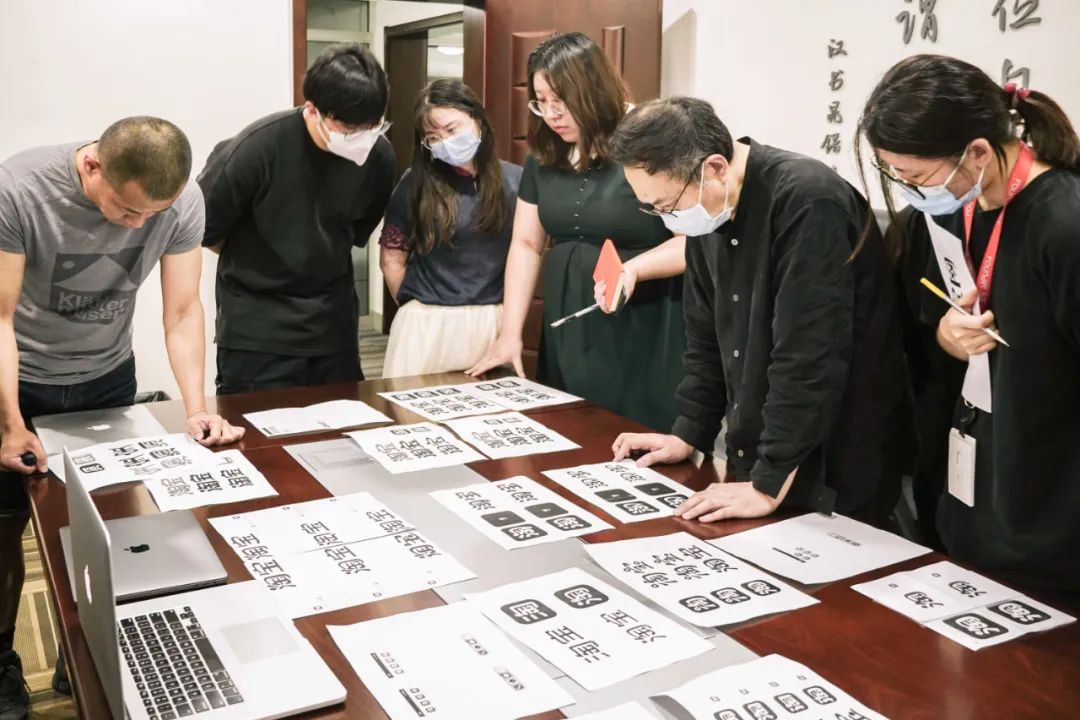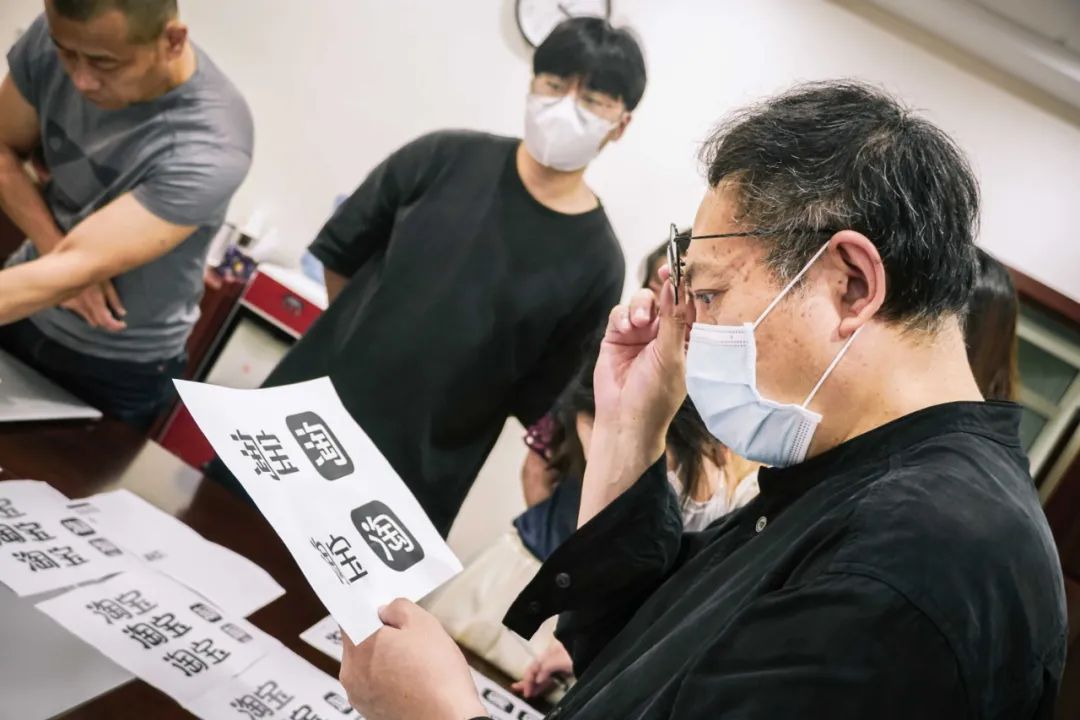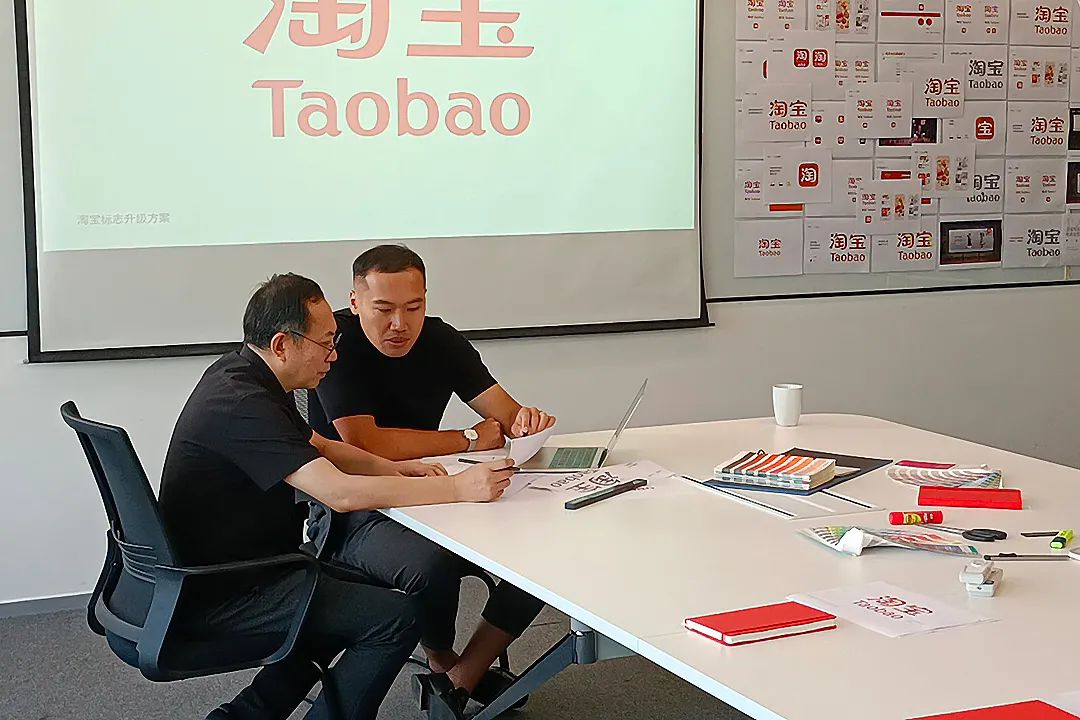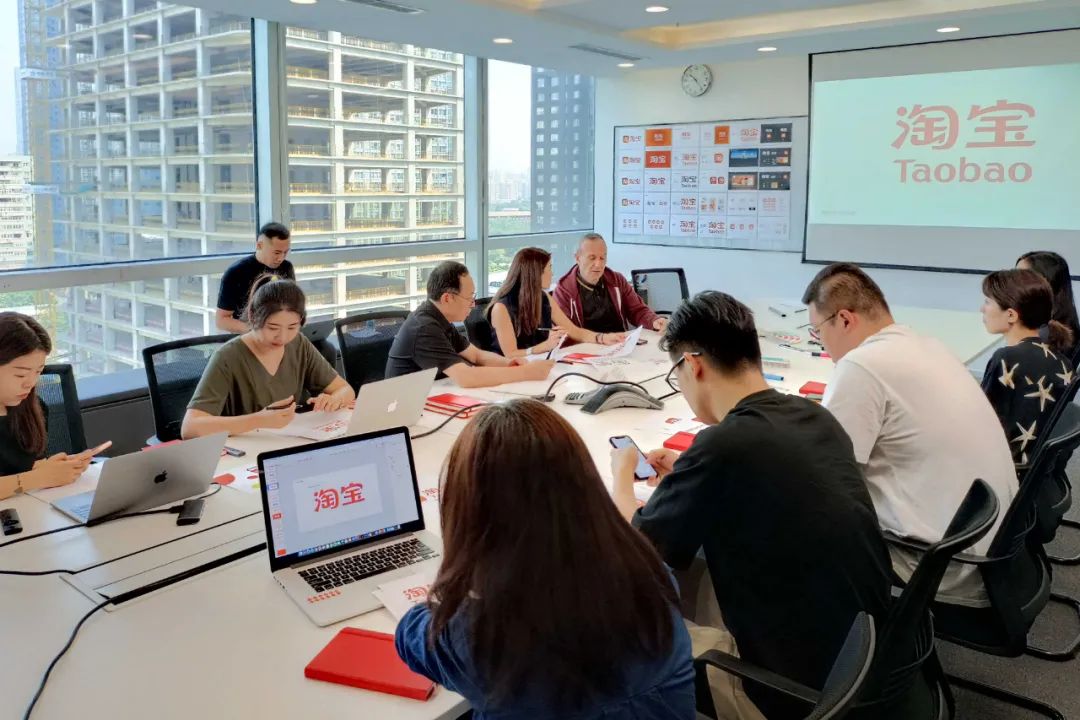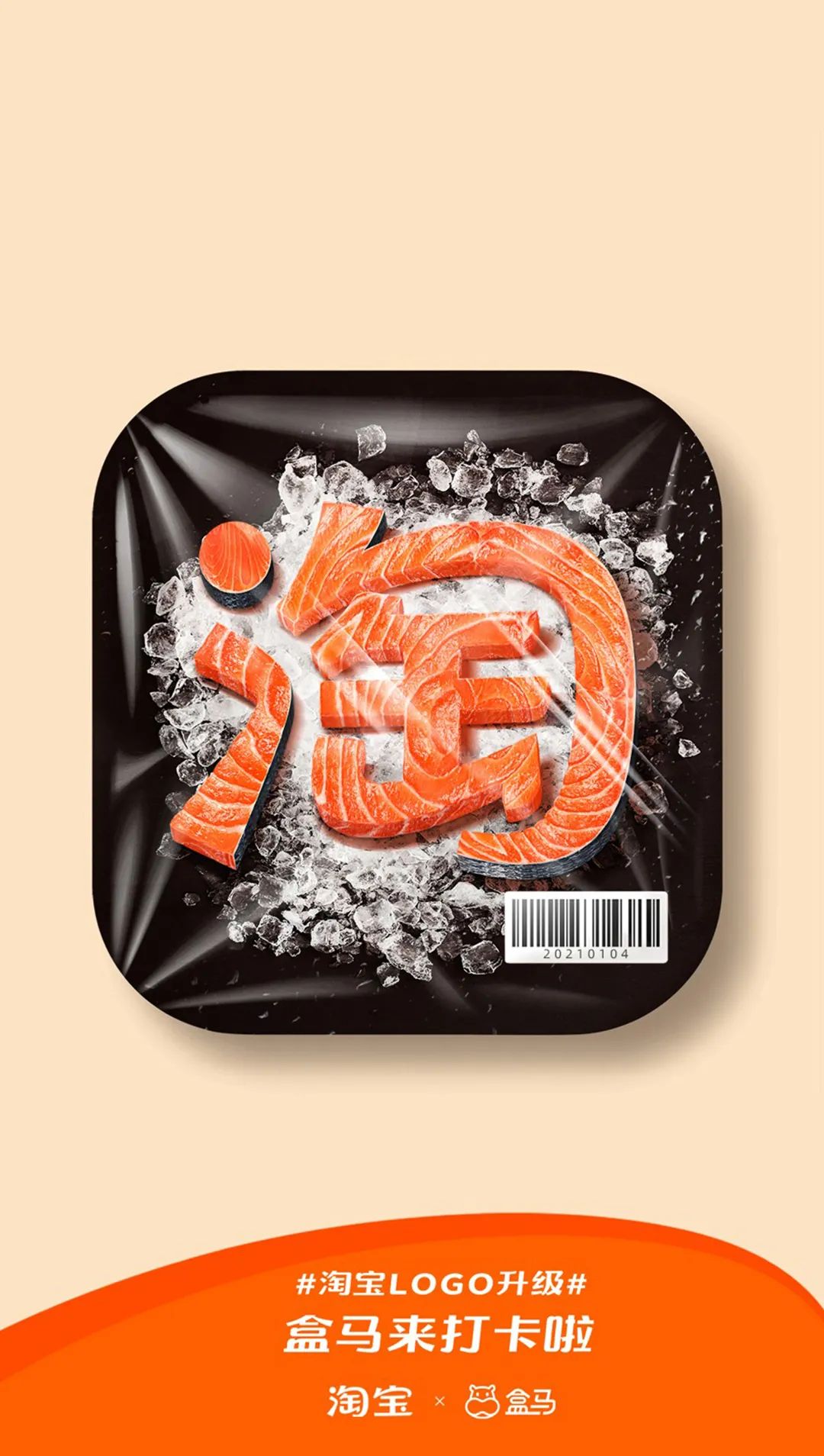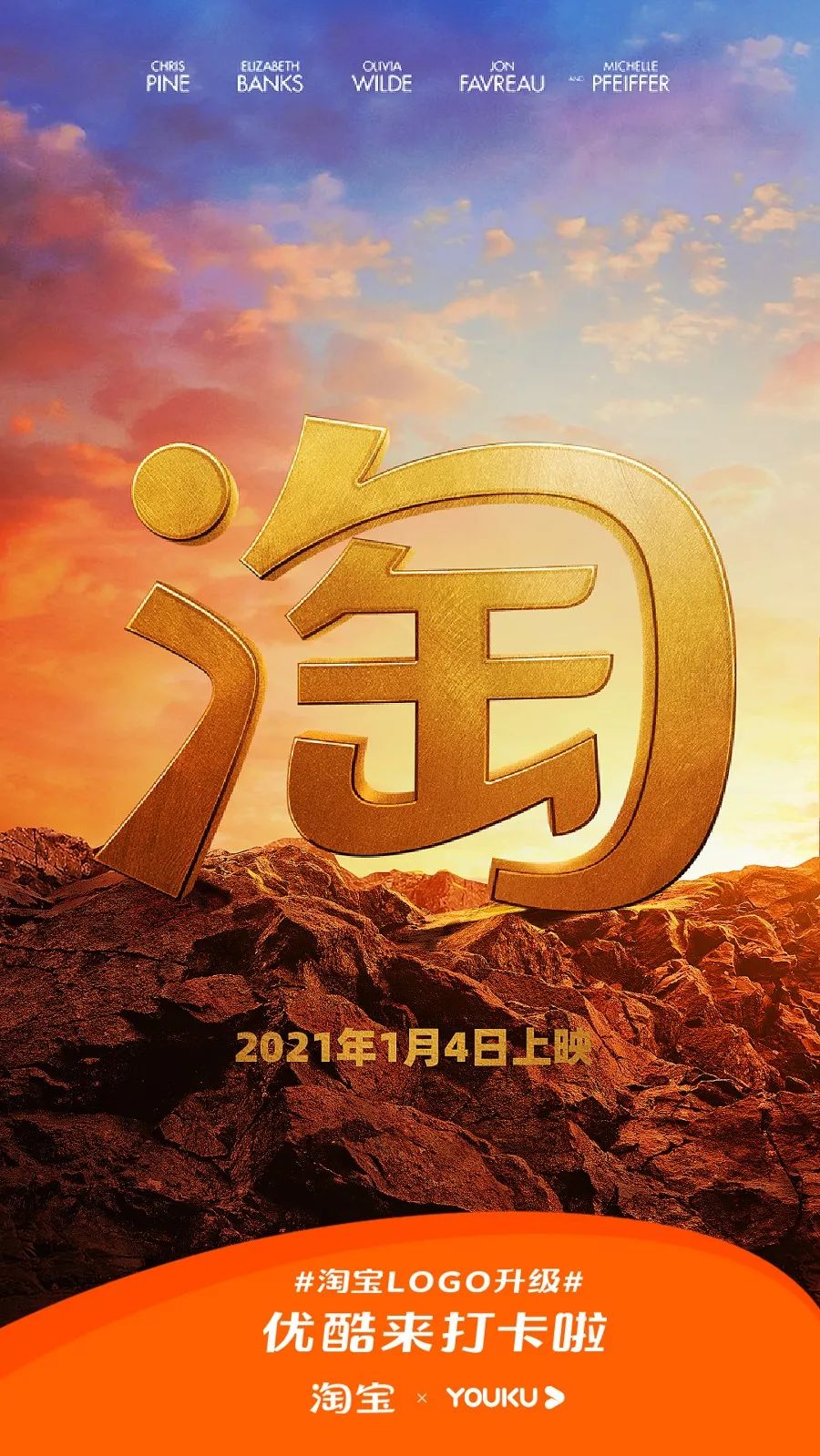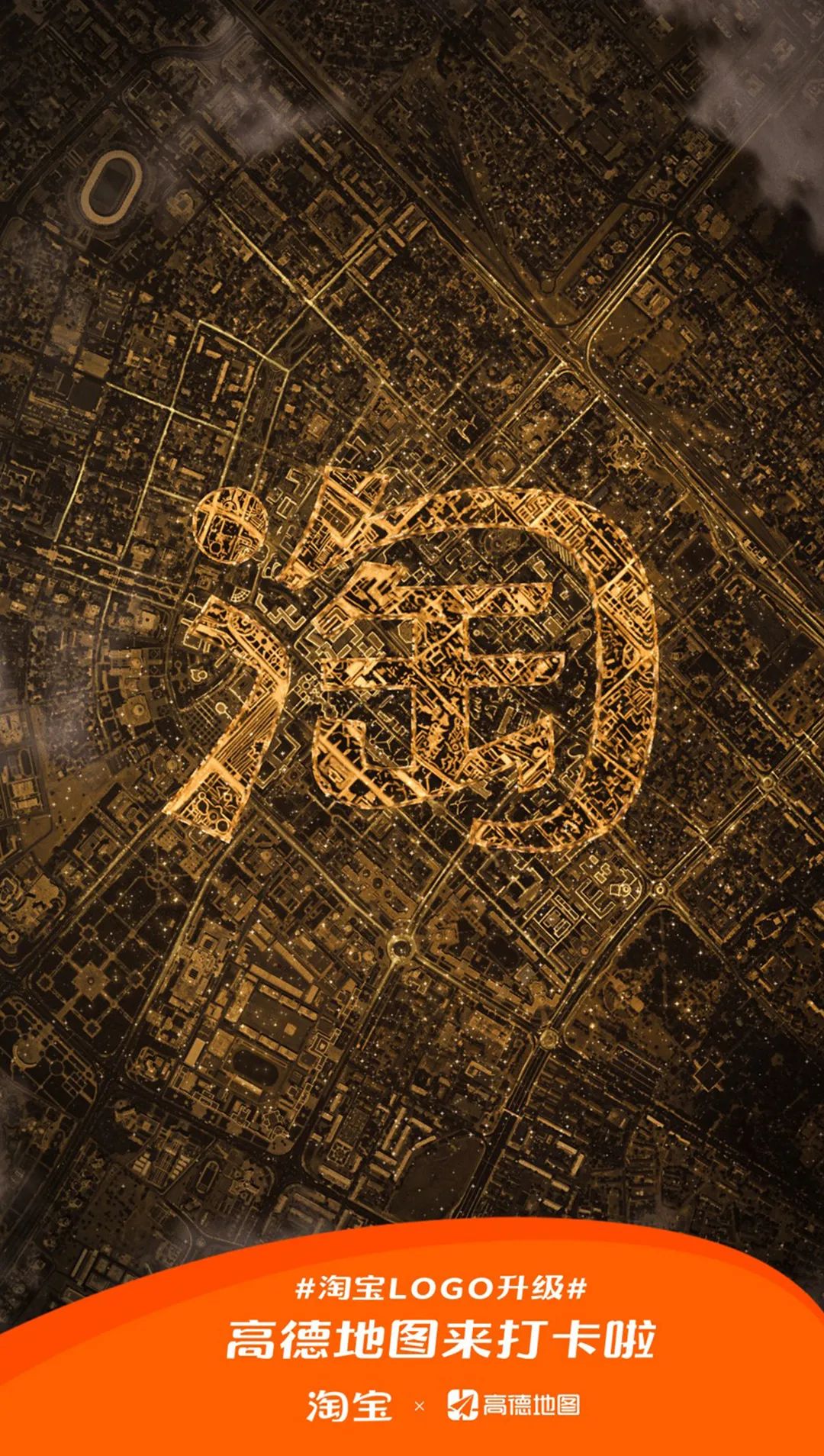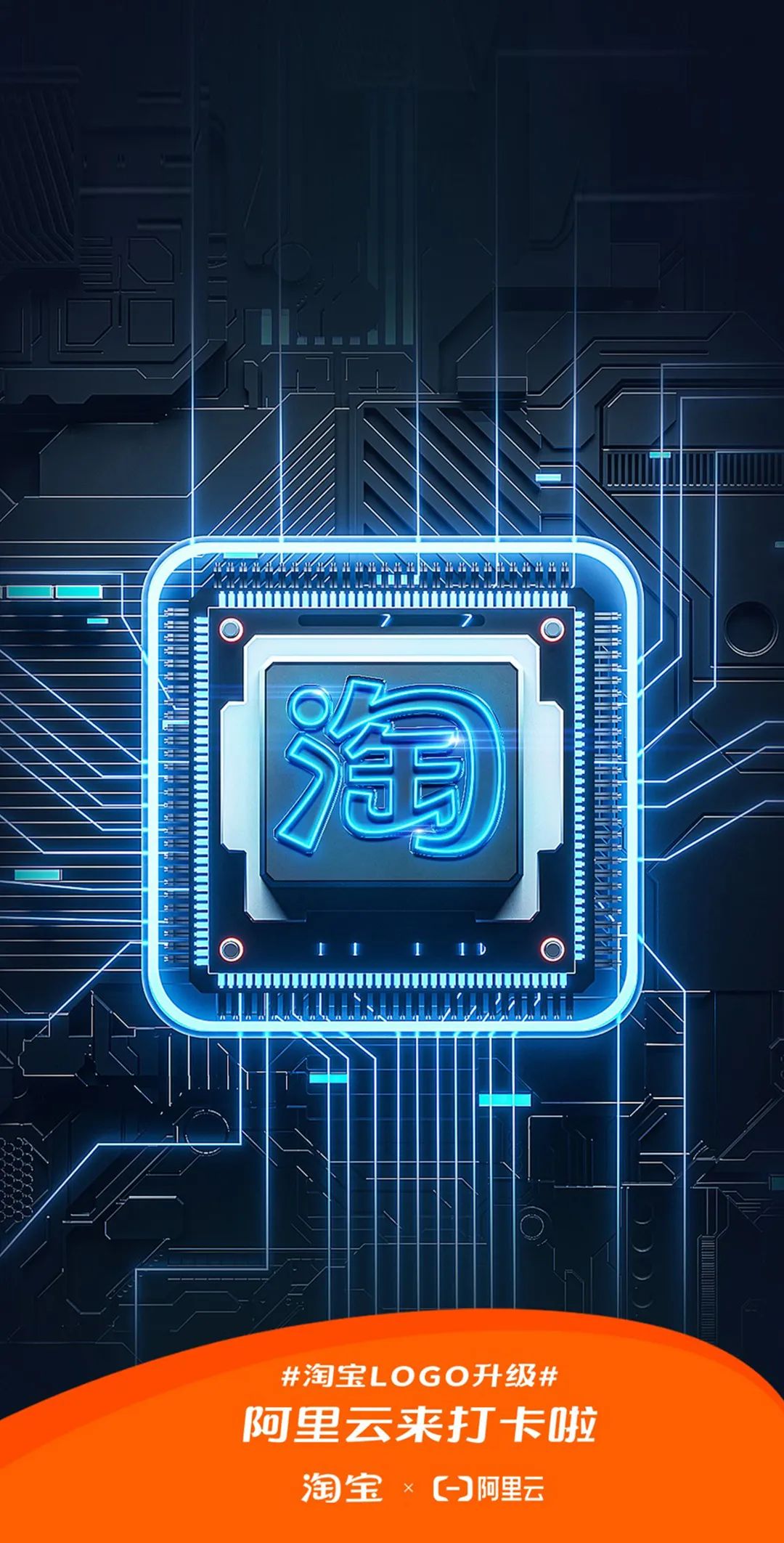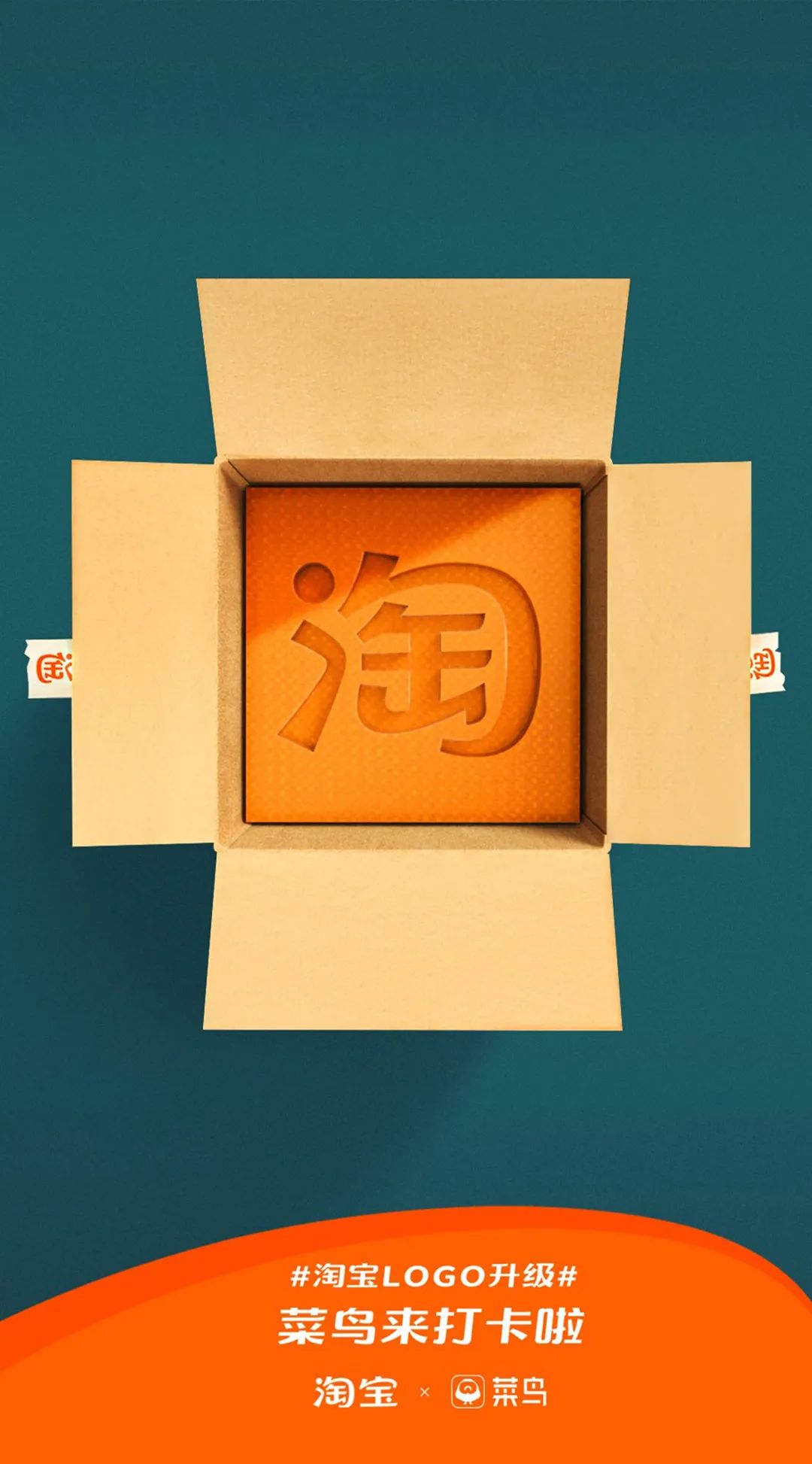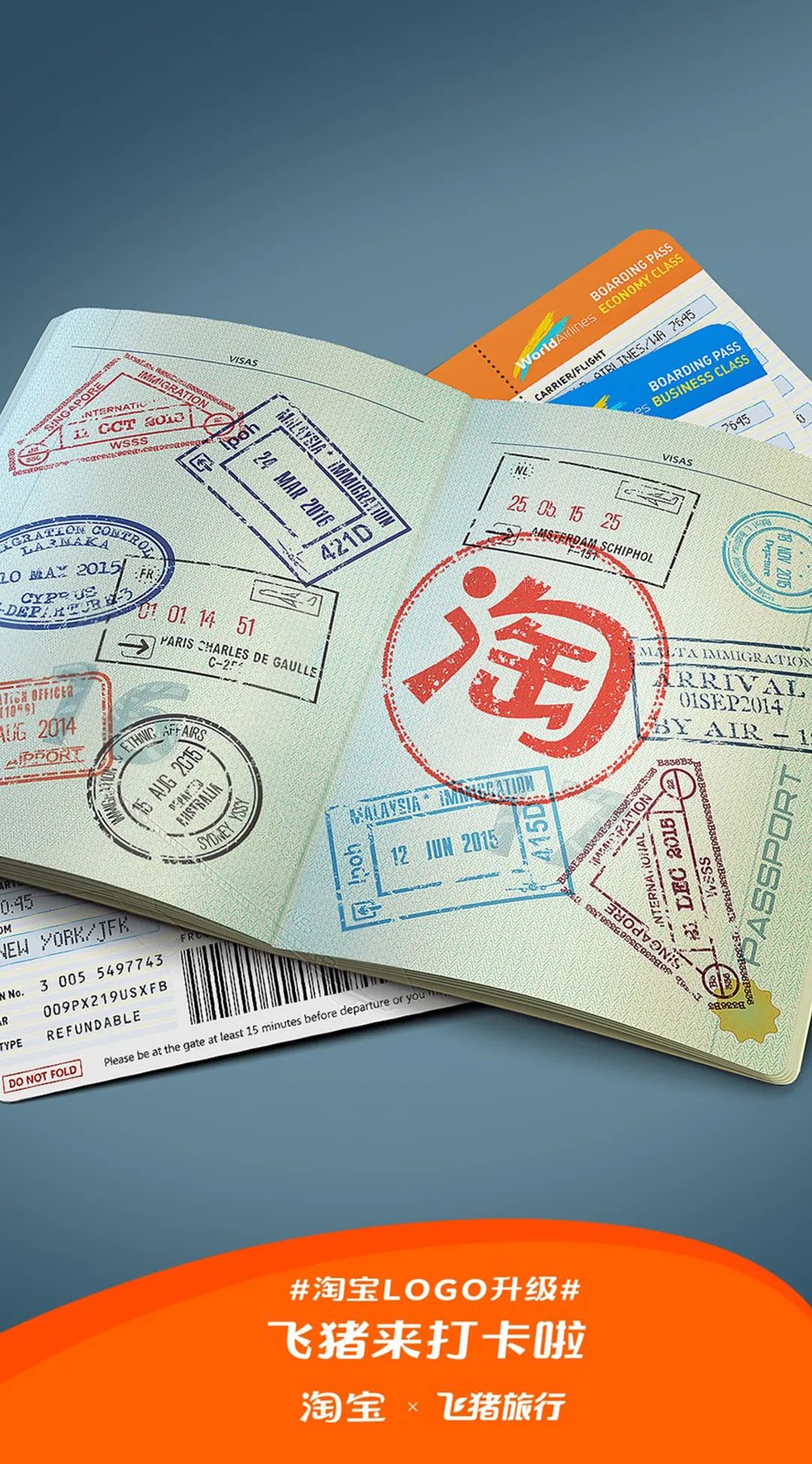
淘宝新logo | 全新“淘宝,taobao”品牌标识发布
全新的2021已经到来,在这个适合展望未来的时候,淘宝也迎来了品牌形象的升级,一个万象更新的淘宝呈现在大众面前。
“淘宝直播很有趣味”,“淘宝人生很新潮”,“淘宝更好逛了”……越来越多的用户在感受淘宝的新变化。新淘宝,让用户在“淘好物”过程中更能感受到“逛”的乐趣,从产品、直播等多场景多维度带给用户全新体验。伴随着产品的升级,全新的“淘宝”品牌形象在设计层面表达了新的内核。
联合设计
此次淘宝品牌LOGO升级,由Alibaba Design、知名品牌设计公司Meta Design、方正字库三方联合完成,在高效的协作沟通下,经过多轮细致地讨论、筛选、修改、打磨,才有了最终的呈现。
设计思路
在新淘宝的大背景下,设计的挑战在于如何将抽象的心智具象表达。此次品牌设计将围绕“连接”“开放”“有趣”三大设计理念透过字体传达淘宝的品牌新内核。
连笔&连接
在新的字体中将有粘连但又不够流畅的笔画结构,让它们“一气呵成”起来,通过连笔来表达“连接”,它寓意了新淘宝要更好地连接商业、用户和内容。
空隙&开放
“通透”是新的字体比较直观的感觉,让字体本身结构上有“呼吸”的空间,它代表了新淘宝对外能够提供充足的空间,同时也将生态体系打开,从而吸收更多的资源共赢共创。
弧度&有趣
新的字体在弯折笔画的连接处做了弧度处理,让整个字体看起来更加有活力,它要展现的是新淘宝将产出更加丰富多样的内容,让消费者能体验到更多趣味且好逛。
中文解读
围绕着上述三大设计理念,全新“淘宝”品牌标识,充分融合了中华传统书法文化和现代的设计语言、设计手法,呈现出多元、丰富、有趣的品牌面貌。
写意&节奏
全新升级的“淘宝”特别注入了自然书写的笔势,将写意融入设计之中。在设计上借鉴了行书的技法,在字体的笔势相承之处运用连笔书写,线条流畅自如,笔画之间气息贯注、流动和谐。
连笔书写
蓄势&能量
字体部件的设计突出了笔画的血脉与气势,字体起笔处注入能量,转折时意气相聚,呈现出蓄势待发的姿态,末尾的钩画收笔果断,整体给人一种势如破竹、一气呵成的视觉感受。
蓄势转折
“淘宝”横画起笔处采取直切手法,如逆锋蓄势,运笔时线条微弧上扬,收笔处笔画轻提,笔势流丽、焕发风采。
横画“左直右弧”,呈上扬趋势
精细&整体
新“淘宝”的设计细节精微生动,通过适当的减细、避让,字体笔画结构紧密得当,布白停匀、筋骨相谐,穿插避让恰到好处。
合理避让
两个单字点画的笔形浑圆一致、遥相呼应,形成左右顾盼的姿态,文字之间脉络贯通,构成一个有机的整体。
点画呼应、左右顾盼
英文设计
升级中英文字标,让形象更统一更聚焦
中英文字标互相呼应;英文字标需要足够简约才能满足LOGO以中文为主,英文为辅的传播需求。
为数字化时代而生
优化LOGO的笔划及布白,提高LOGO在数字端上小尺寸下的可识别度。
当淘宝的中文字标设计逐渐成型,承载着相同设计理念的英文字标也应运而生。
“T”的横画呼应中文的横划特征:微弧上扬,以流畅的圆角收笔
“a”维持双层结构,与相邻的“o”更能区分,保持高的视别度;顶部的拱形弧线与淘字的“勹”部笔势互相呼应
开放“o”字的内白,平衡笔划粗细的变化;确保外轮廓的弧线图滑流畅,使造形更丰富生动
升级后的英文字标彰显中文字标的设计精髓,与时并进
新淘宝,新品牌,新形象。为了能够让用户对于品牌有更具体的认知,此次品牌升级还创造了淘宝自己的超级符号,结合业务丰富的场景,让视觉语言更具专属性和多样性,让用户更好的感知到,一个更连接用户、更开放平台、更充满趣味的新淘宝正在走来。